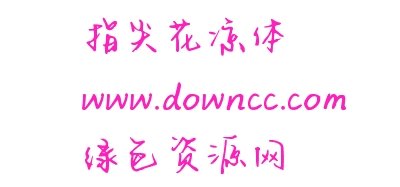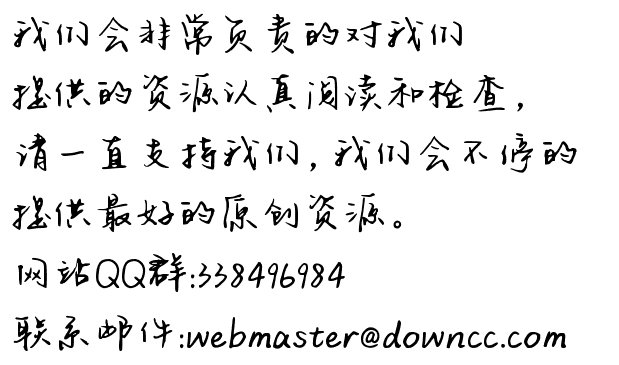
指尖花涼體是一款浪漫溫柔的手寫字體,字跡清晰而濃黑,給人直觀的視覺呈現(xiàn),文字繾綣間更顯的獨(dú)特矚目,綠色資源網(wǎng)今日推薦!
“指尖花涼憶成殤。”——指尖花涼體。
本字庫是在國家標(biāo)準(zhǔn)簡體字庫GB2312所包含6763漢字的基礎(chǔ)上,又增加了近200常用字,已經(jīng)覆蓋了大陸99.75%的漢字使用頻率,足以滿足日常需求。
指尖花涼體藝術(shù)效果十分出色,讓文字擁有不同的表達(dá)方式,可以廣泛用于平面設(shè)計(jì)、藝術(shù)設(shè)計(jì)等多種方面。